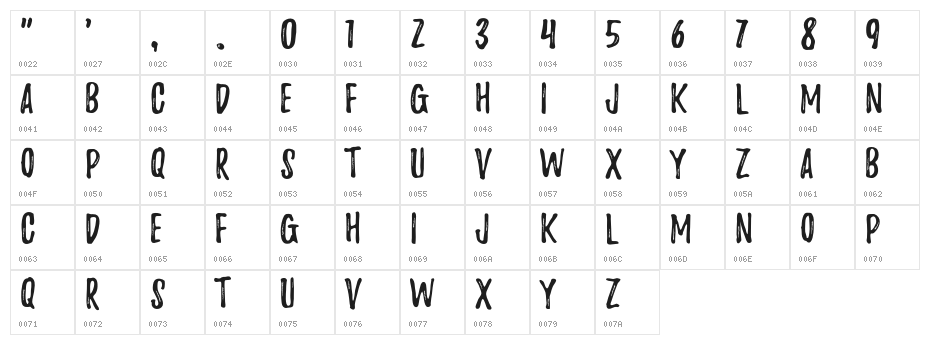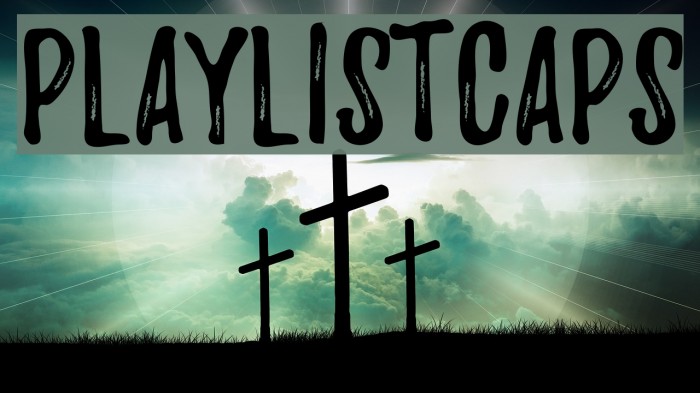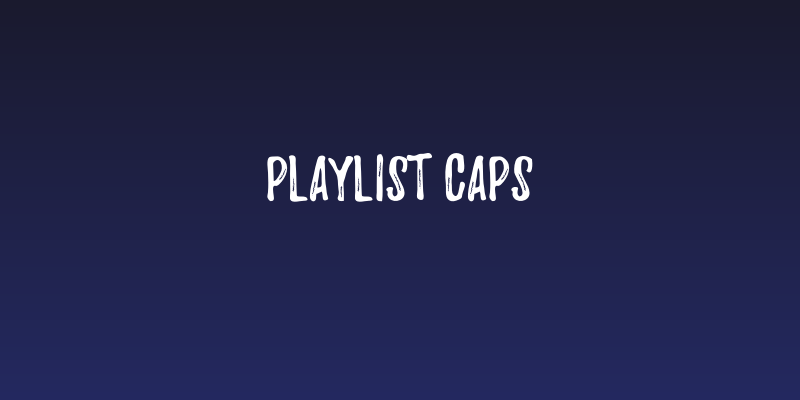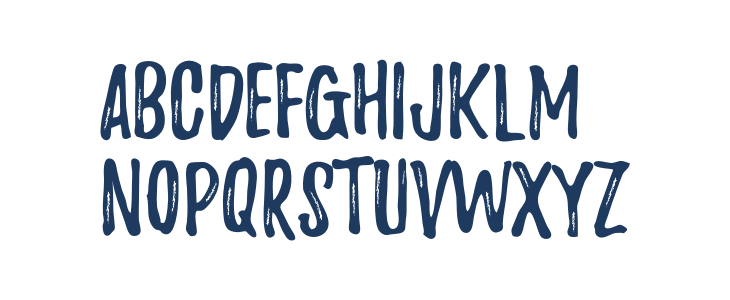
Playlist-Caps Font
| Progetti proposti | Ideal for creative projects such as posters, invitations, branding, and social media graphics where a personal and artistic touch is desired. |